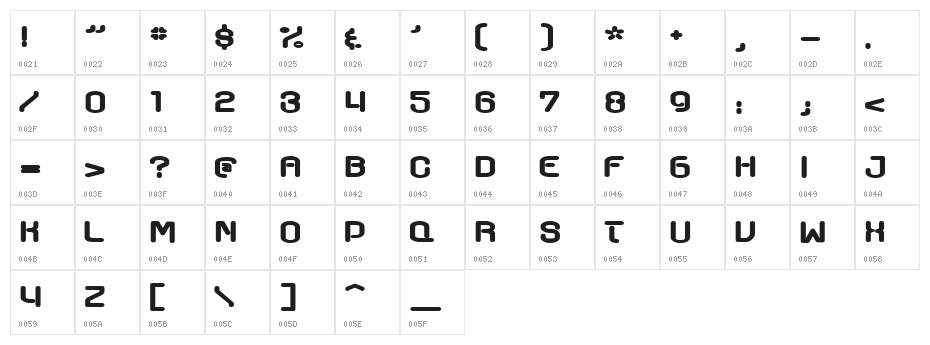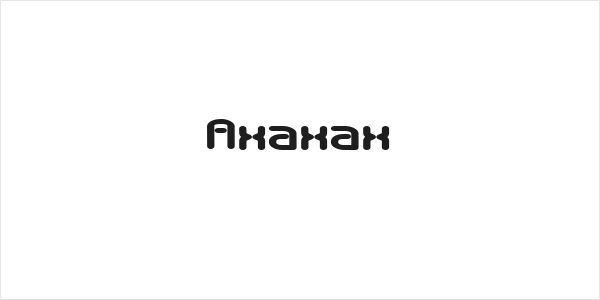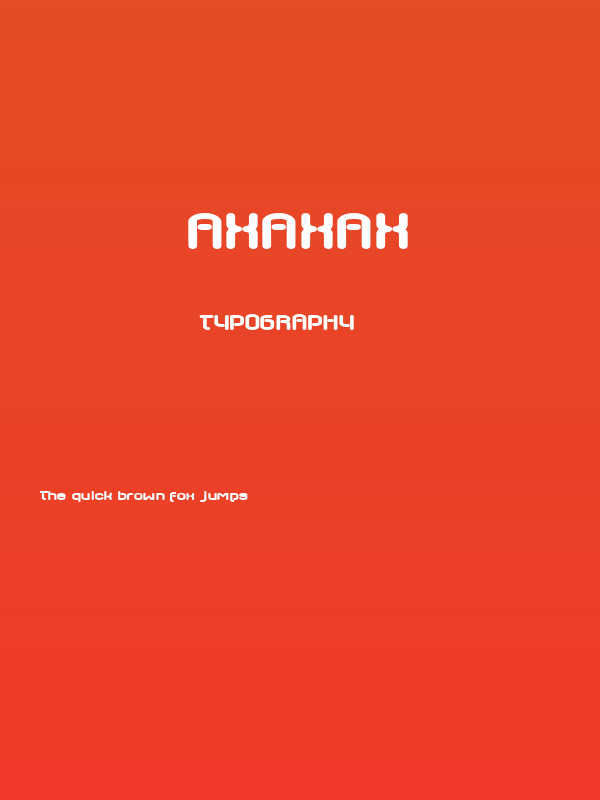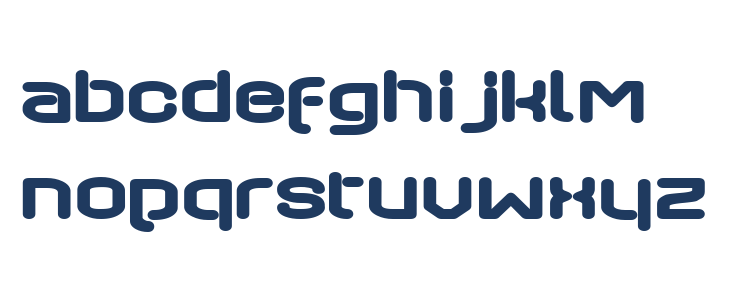
Axaxax Font
| Caso d'uso | Headlines, Logos, Digital interfaces |
| Progetti proposti | Ideal for tech branding, digital interfaces, futuristic designs, and creative projects. |